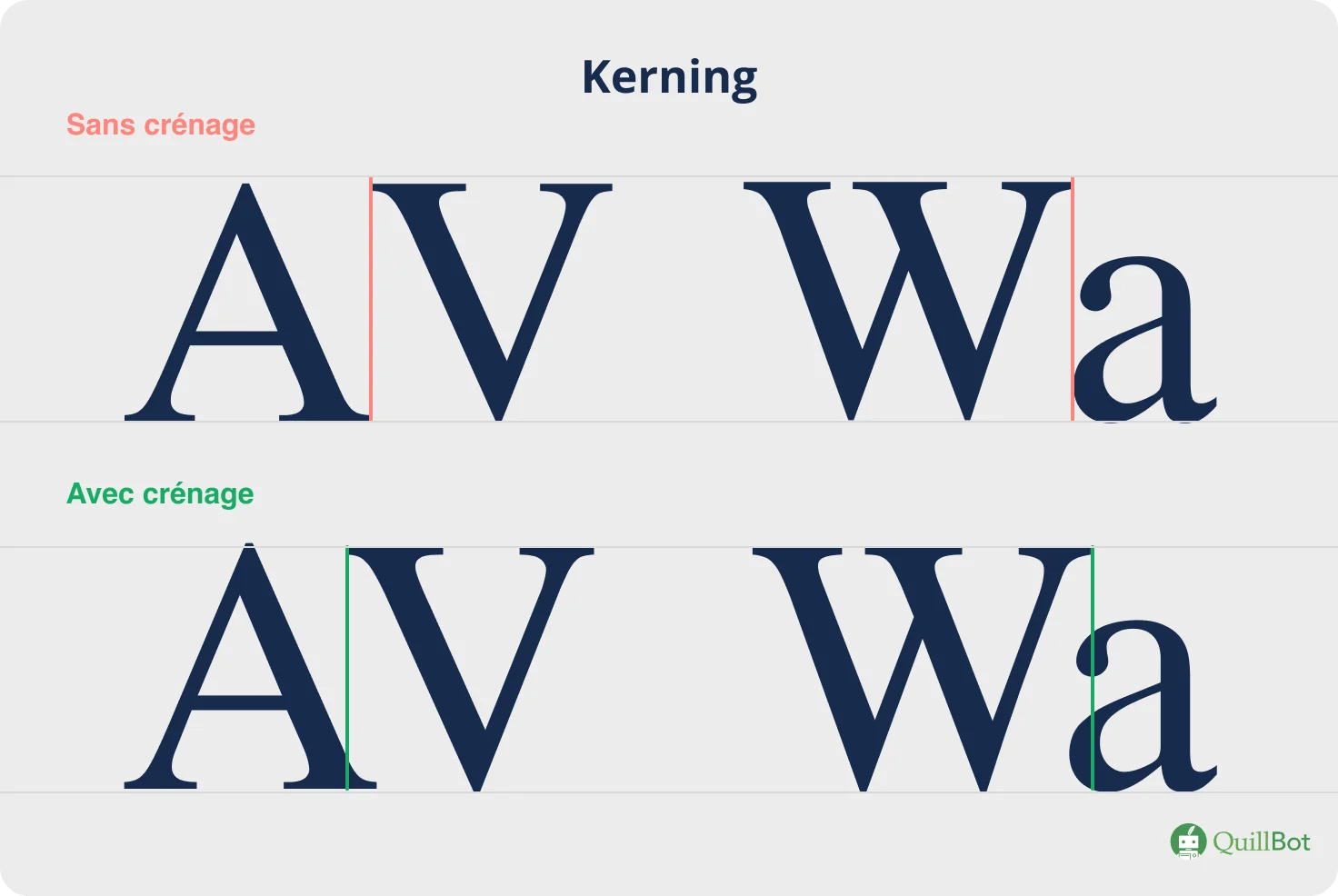
Kerning (ou crénage) | Définition
En typographie, le kerning, terme anglais, désigne l’ajustement de l’espace entre deux caractères.
Opposé à l’approche uniforme, le crénage, équivalent français, privilégie l’approche de paire en mettant l’accent sur la relation unique qui existe entre des caractères successifs.
Espace, approche, crénage sont autant de notions typographiques dont la maîtrise est essentielle pour la création d’une identité visuelle unique. Si le crénage participe à rendre une marque inoubliable, une bonne typographie, elle, sait se faire oublier…
Kerning, crénage, approche de paire : 3 termes, une même définition
Le crénage, aussi désigné par le terme kerning en anglais, est une approche typographique de paire. Elle permet d’ajuster le blanc, ou l’espacement, entre des paires de lettres, notamment lorsque la police utilisée est une police à chasse variable.
• glyphe : dessin du signe typographique (caractère, diacritique, ligature, etc.),
• approche : espaces fines ajoutées de chaque côté du glyphe,
• chasse : largeur du glyphe d’un caractère, comprenant ses deux approches,
• fonte : ensemble des glyphes (lettres et signes) composant un caractère complet.
Dans une police dont la chasse est invariable, le glyphe et ses espaces latérales sont les mêmes. Dans une police à chasse variable, les espaces de part et d’autre du glyphe varient en fonction de chaque glyphe.
Un crénage régulier permet un espacement identique entre chaque paire de glyphes, quelle qu’elle soit. Ainsi, dans une police de caractères créée par un professionnel, le graphiste décide du crénage pour chaque paire de caractères, une à une.
Aujourd’hui, les outils informatiques, notamment les logiciels de gestion de fonte, le font automatiquement. Toutefois, le résultat est loin d’être satisfaisant, car le crénage uniforme n’est pas spécifique à chaque paire de lettres.
Dans l’approche par paire, le graphiste teste toutes les associations possibles de paires de caractères pour en régler les espacements. La paire de lettres « ab », puisqu’elle diffère de la paire de lettres « ba », n’aura pas le même espacement avant et après chaque glyphe.
L’approche typographique améliore grandement la lisibilité des caractères en espaçant chaque glyphe selon le caractère qui le suit ou le précède.
Au temps des caractères d’imprimerie en plomb, ces blancs étaient identiques. Chaque approche, qu’elle soit gauche ou droite, affichait la même largeur, tout comme son équivalent vertical, le talus de tête ou de pied, respectivement au-dessus ou en dessous de la ligne de base.
Parallélépipèdes, les petites pièces métalliques des premières presses européennes ont d’abord présenté une forme carrée pour devenir rectangulaire lorsque le talus et l’approche ont changé d’épaisseur.
Aujourd’hui, l’approche par paire se confond avec le crénage. Toutefois, techniquement, le crénage consiste en l’ajustement de l’approche d’un seul des deux caractères de la paire pour corriger son interlettrage, la somme de toutes les approches de la paire.
Quelle que soit la terminologie adoptée, retenons simplement que chacune de ces techniques modifie l’espacement entre deux glyphes successifs.
Ainsi, l’essence des polices à chasse variable réside dans ce détail typographique : l’espacement n’est pas unique au glyphe, mais résulte de la combinaison des différentes formes de caractères.
Par ailleurs, certains caractères de ces polices ne possèdent pas du tout d’approche : les ligatures (« æ » ou « œ ») et les consonnes doubles (« tt » ou « ff ») se touchent physiquement pour ne former qu’une seule et même lettre.
Kerning et tracking : différences
Aujourd’hui, les outils de PAO (publication assistée par ordinateur) permettent de modifier l’esthétique générale d’un texte en utilisant à la fois le kerning, ou l’approche de paire, et le tracking, ou l’approche de groupe, au sein d’un même texte.
Si l’approche de paire ajuste l’espacement entre deux caractères successifs spécifiques, l’approche de groupe modifie les espaces entre les mots et les lignes.
Différences kerning/tracking
• Kerning : ajustement spécifique entre deux glyphes (approche de paire).
• Certaines paires de caractères, comme les lettres « AV », doivent afficher une espace ni trop étroite ni trop large entre les lignes obliques pour les distinguer rapidement d’une ligature (« Æ » par exemple), sans les confondre avec une abréviation, notamment celles du nom commun avenue ou de la préposition avant.